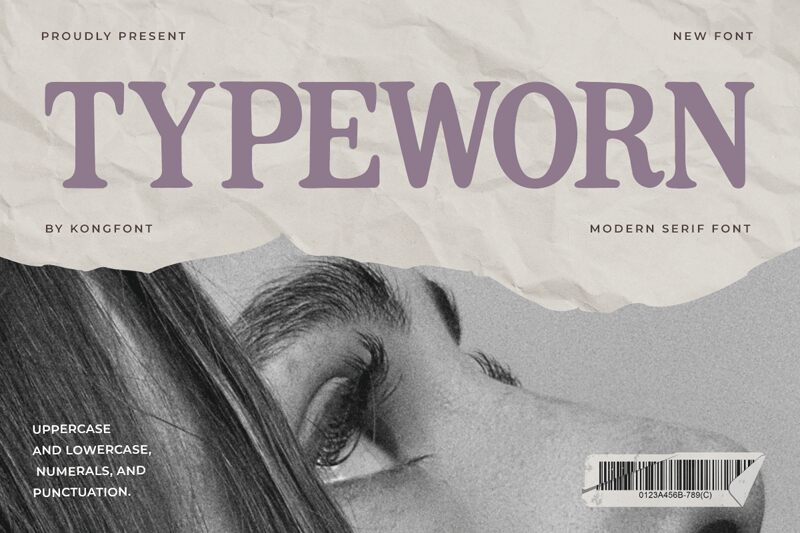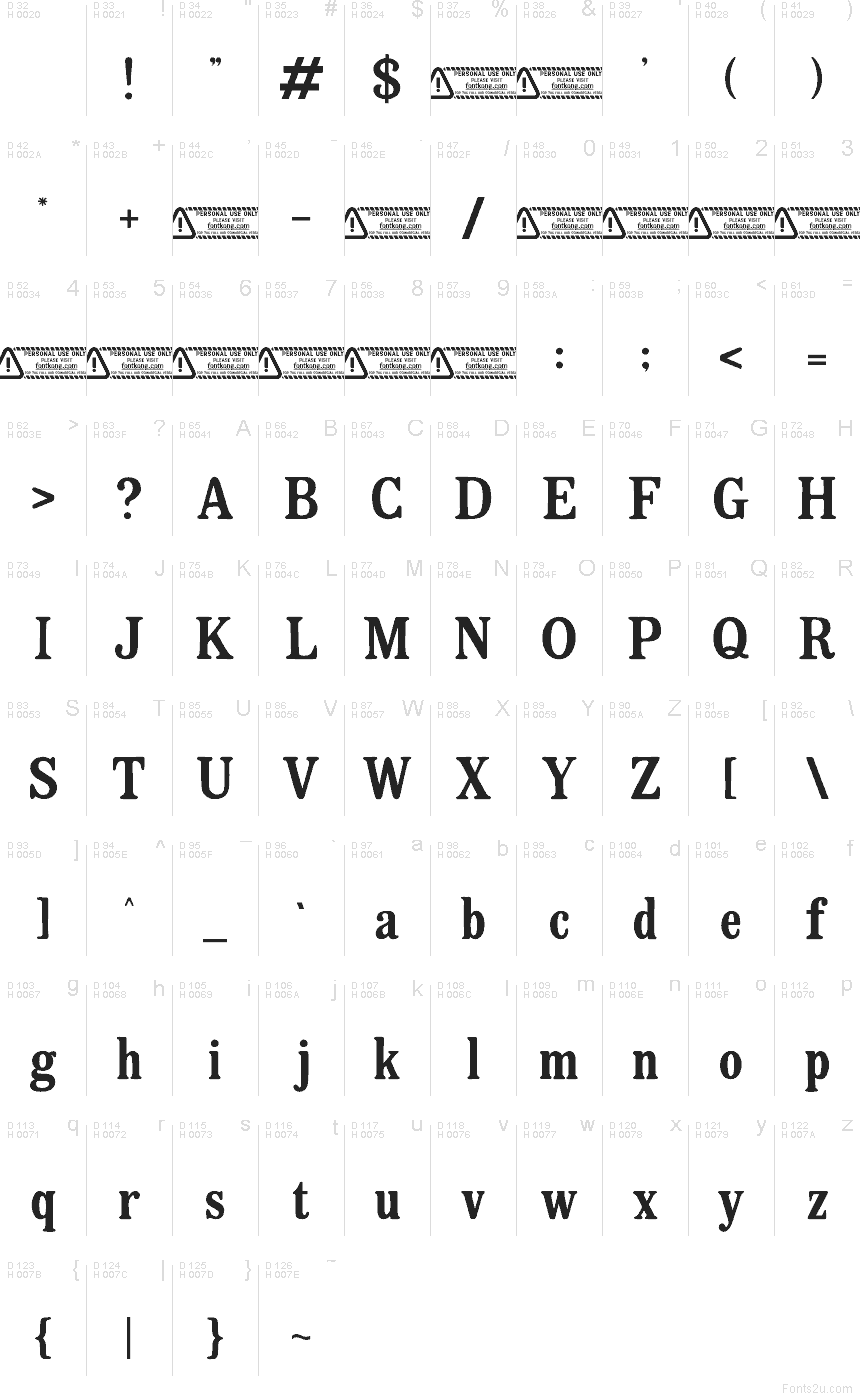
Typeworn by Kong Font ist eine kostenlose Serifenschrift mit verwittertem, charmantem Old-Print-Charakter. Die Buchstaben wirken an den Kanten leicht abgerieben und unregelmäßig, was dem Font eine authentische, menschliche Textur verleiht. Gleichzeitig sorgen die breiten Serifen und tiefen Schwünge für eine klassische, buchdruckähnliche Ästhetik.
Die Schrift eignet sich perfekt für Verpackungen, Café-Menüs, Plakat-Überschriften, Buchcover und redaktionelle Headlines, bei denen ein Hauch von Nostalgie erwünscht ist, um die Botschaft bodenständig wirken zu lassen. Als kostenlose Schrift ist sie zudem ideal für Etiketten, Zitate und kurze Branding-Elemente, da die abgenutzte Serif-Oberfläche selbst einfachen Wörtern eine subtile Letterpress-Anmutung verleiht.